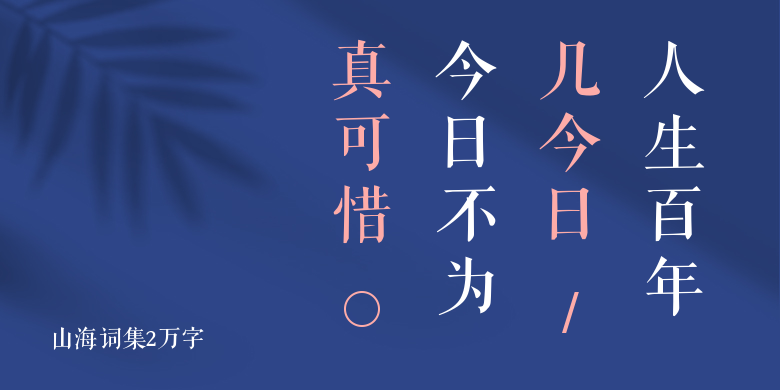
山海词集2万字
山海词集2万字,这款字体结构工整、笔画清晰,兼顾美观与易读性,适用于标题、正文、海报、包装、LOGO 等多种场景。字形优雅稳定,风格百搭耐看,适配日常排版与创意设计,让文字呈现更舒适、更具质感。山海词集2万字一笔一画,皆是细节,以均衡的比例、流畅的线条打造舒适视觉体验,字形端正大气,风格简约现代。无论是商业设计、品牌宣传还是日常排版,都能轻松驾驭,让文字更有格调与力量。山海词集2万字字体下载。